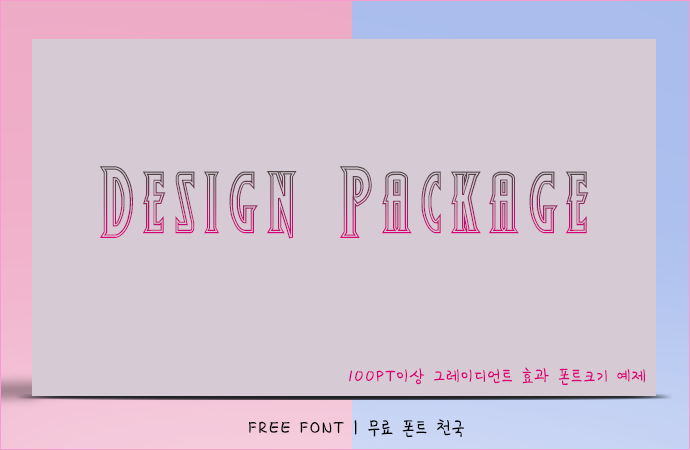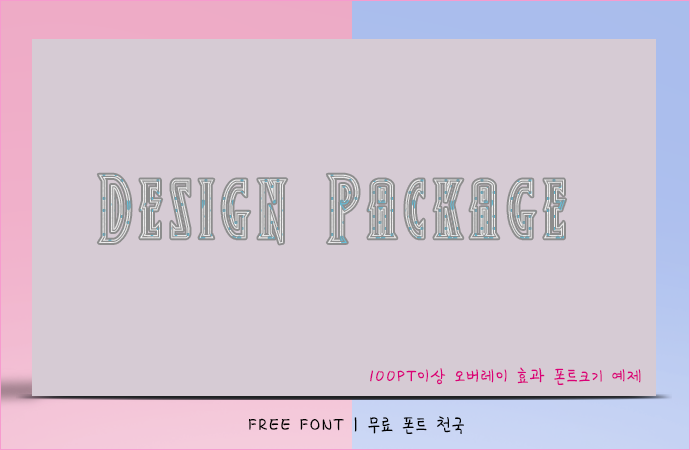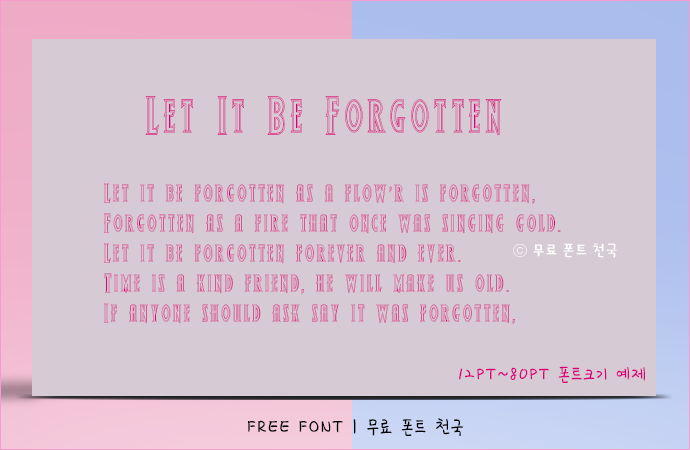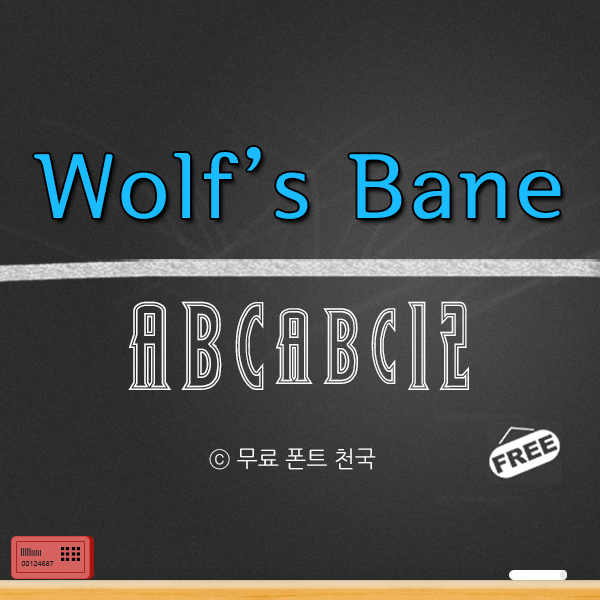
아웃라인 형태의 'Wolf's Bane Outline' 영문폰트
Wolf's Bane Outline 폰트 정보
가독성은 떨어지지만 포토샵에서 별도의 효과를 주지 않아도 아웃라인 형태의 서체를 표현할 수 있는 Wolf's Bane Outline 서체입니다. 서체 특성상 알파벳 간격이 매우 작아 포토샵으로 일정한 간격을 늘려 주는 옵션을 필수로 적용해주셔야 서체를 보기좋게 만들 수 있습니다.
Wolf's Bane Outline 폰트 # 미리보기
Wolf's 폰트, 12~80PT 크기로 적용한 효과
Wolf's 폰트, 100PT 크기 이상으로 작업한 오버레이 효과
Wolf's 폰트, 100PT 크기 이상으로 작업한 그레이언트 효과